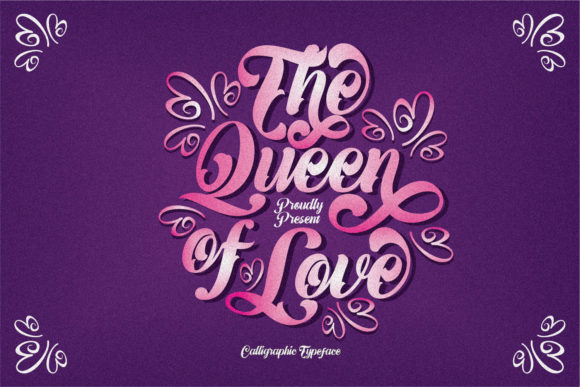
[Creativefabrica] The Queen of Love Font
Королева любви чувствует себя невероятно элегантной и струящейся. Он выглядит потрясающе на свадебные приглашения, благодарственные открытки, цитаты, поздравительные открытки, логотипы, визитные карточки и любой другой дизайн, который нуждается в рукописном прикосновении. Он имеет различные базовые, плавные линии, великолепные глифы и потрясающие альтернативы.